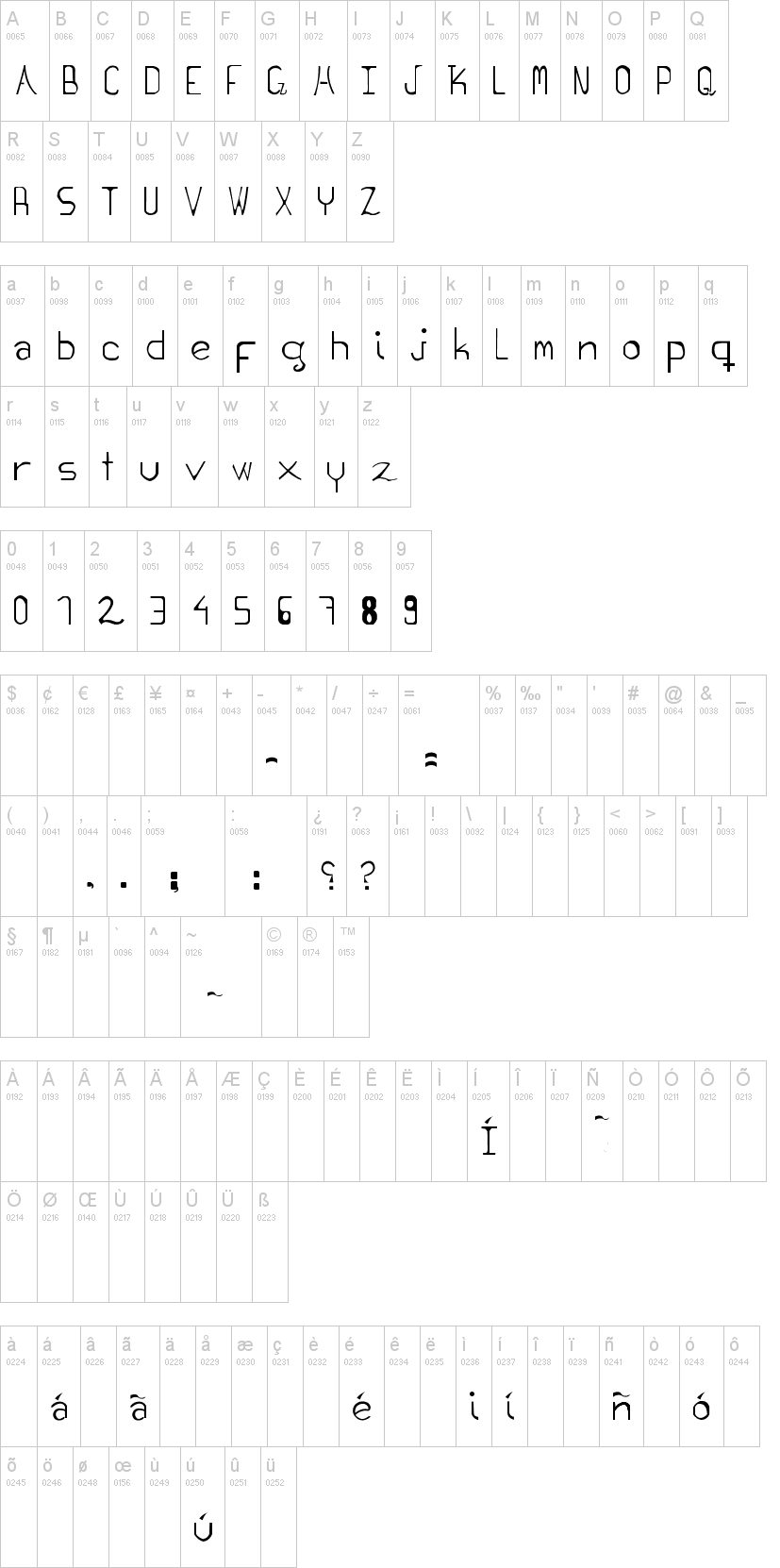
Reading point
Reading point 字体是一款由英国设计师David Jonathan Ross 创作的字体,它是一种新的几何字体,具有独特的外观和感觉,非常适合用于各种现代设计中。Reading point 字体重点关注字母的细节,它的字符有着清晰的边缘,易于识别,并且拥有足够的空间来显示单词的完整性,使得文本易于阅读。它的几何形状和细节使它看起来像一种抽象的艺术,而不是一种传统的字体。Reading point 字体适用于各种现代设计,包括标题、标签、海报、海报、品牌标识等,可以帮助您的设计脱颖而出。
Reading point是一款非常不错的手写艺术字体,具有很好的视觉感,适合于文化类的宣传设计、商业类品牌的广告和产品包装设计以及个性化文字排版等较多场景。